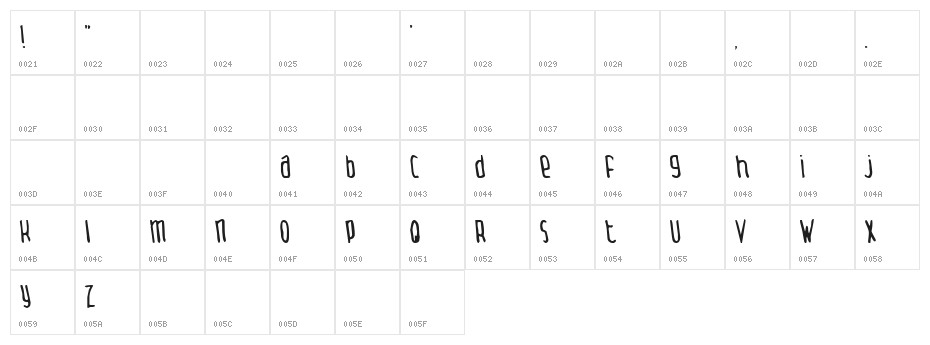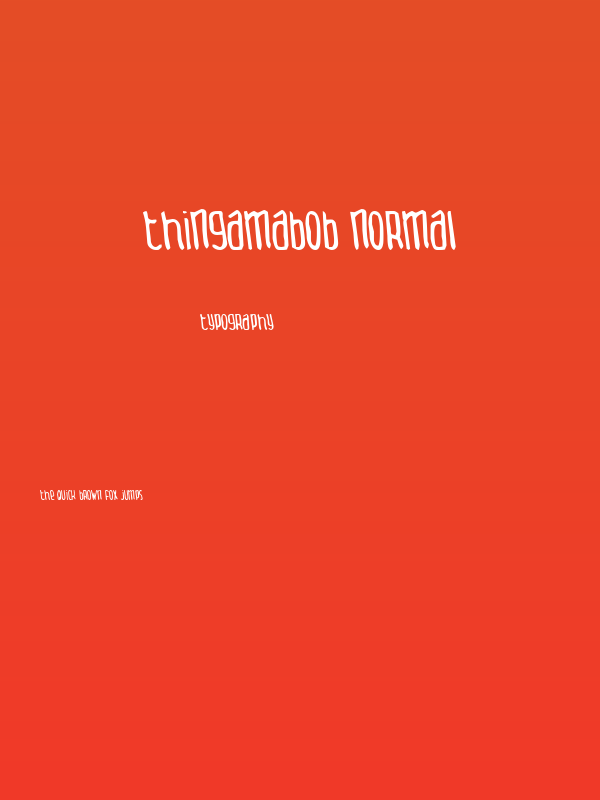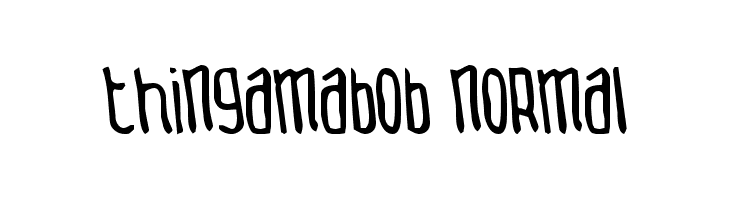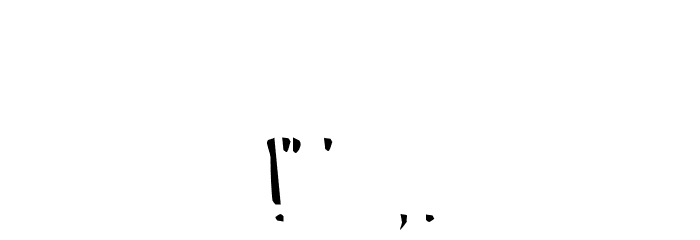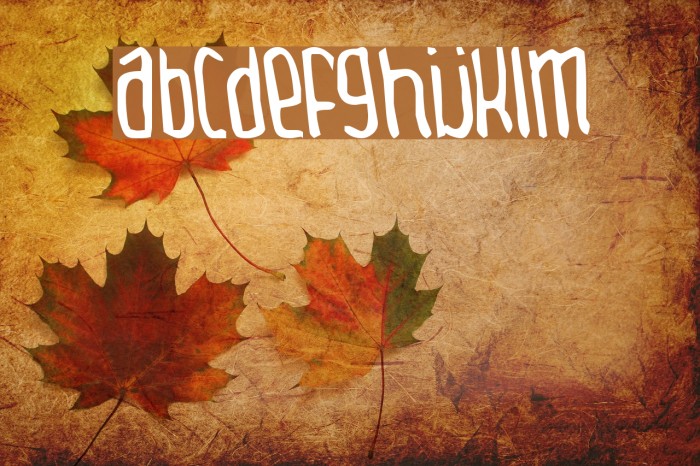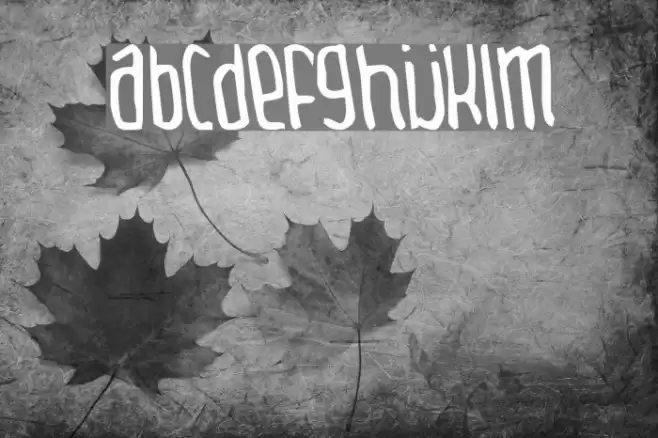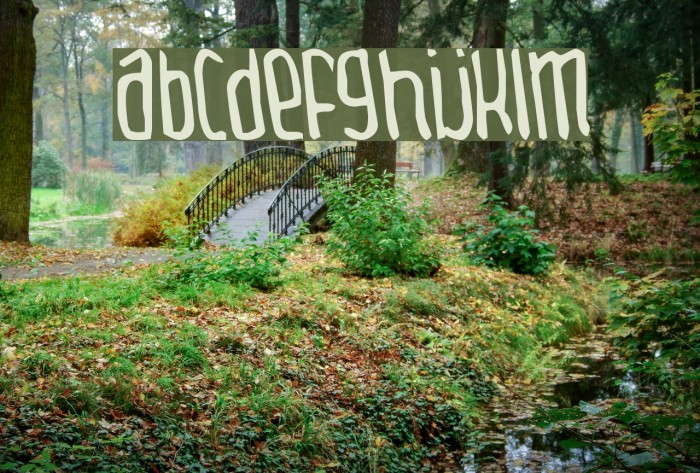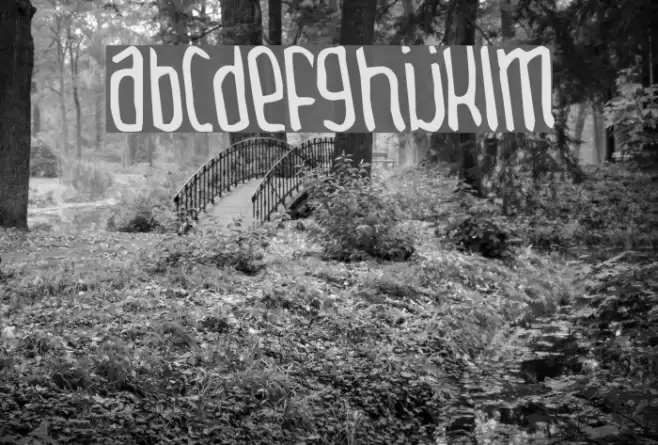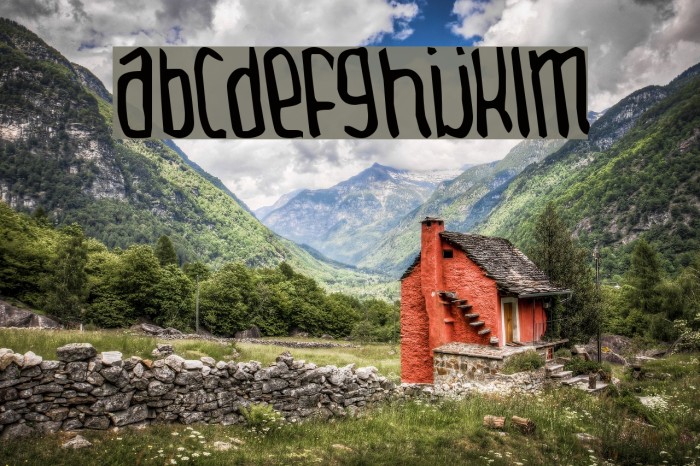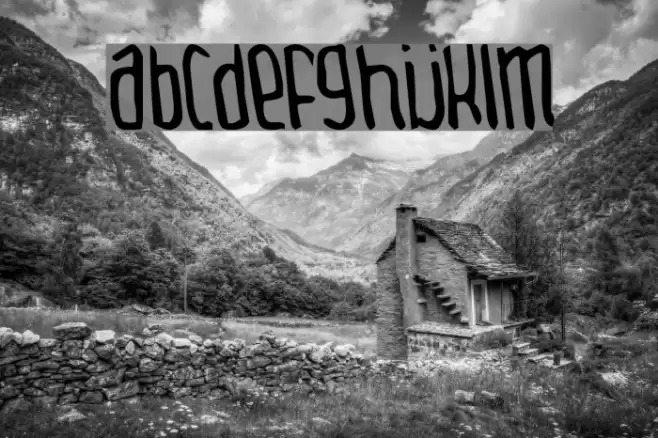
Thingamabob Normal Font
| Gesamtstil | Playful, Quirky, Hand-drawn |
| Vorgeschlagene Projekte | Ideal for children's books, creative posters, playful branding, and informal invitations. |